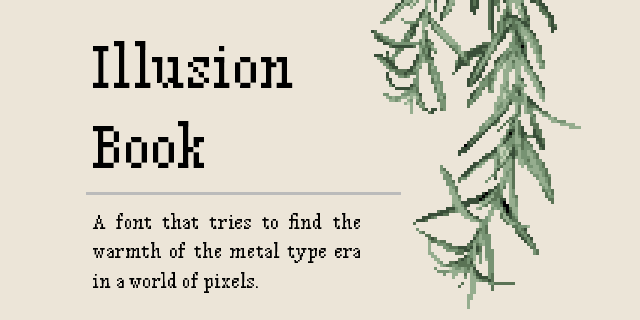
幻象像素书体
别称:Illusion Book
幻象像素书体 Illusion Book
一款尝试在像素世界中寻铅字时代的温润的字体。
涵盖的字符集 Covered Character Sets
- 基本拉丁语
- 拉丁语增补
- 拉丁语扩展-A
- 希腊语和科普特语
- 西里尔字母
- 西里尔字母补充;
以及零星的
- 拉丁语扩展-B
- 拉丁语扩充增补
- 广义标点
- 货币符号
- 类似字母的符号
- 数学运算符。
OpenType 特性 OpenType Features
- 标准连字liga
- 自由连字dlig
- 历史连字hlig
- 斜线零zero
- 小型大写smcp
- 大写转小型大写c2sc
- 旧式数字onum
- 历史形式hist
- 上下文替换calt
- 词尾样式fina
- 花饰字swsh
- 字偶距kern
尺寸 Size
该字体基于 12px 的大小设计。
字体的 UPM(Units Per Em,每个字面框包含的设计单位的数量)按照像素尺寸的 100 倍来转化,即:1 px = 100 units 。
该字体的 UPM 为 1200,故为了保证最佳的渲染效果,请以 12 的整数倍对字体进行缩放。